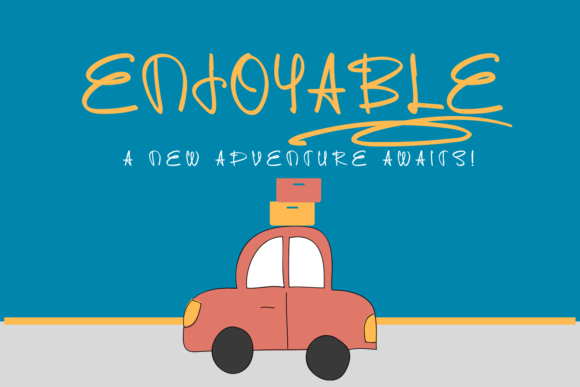
[Creativefabrica] Enjoyable Font (2021)
Enjoyable - это игривый и причудливый шрифт.
Если вы используете его для рукоделия, цифрового дизайна, презентаций или создания поздравительных открыток, он идеально подходит!